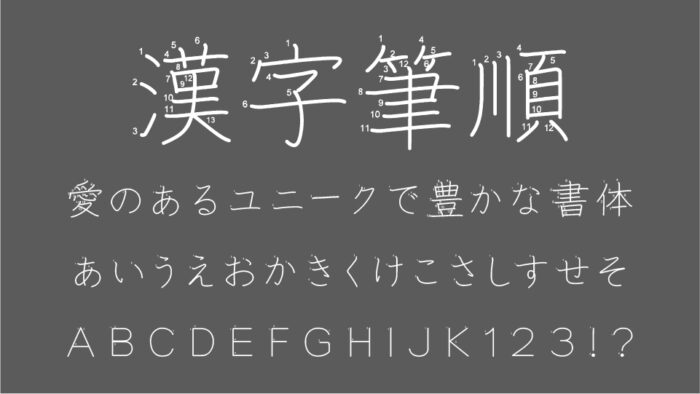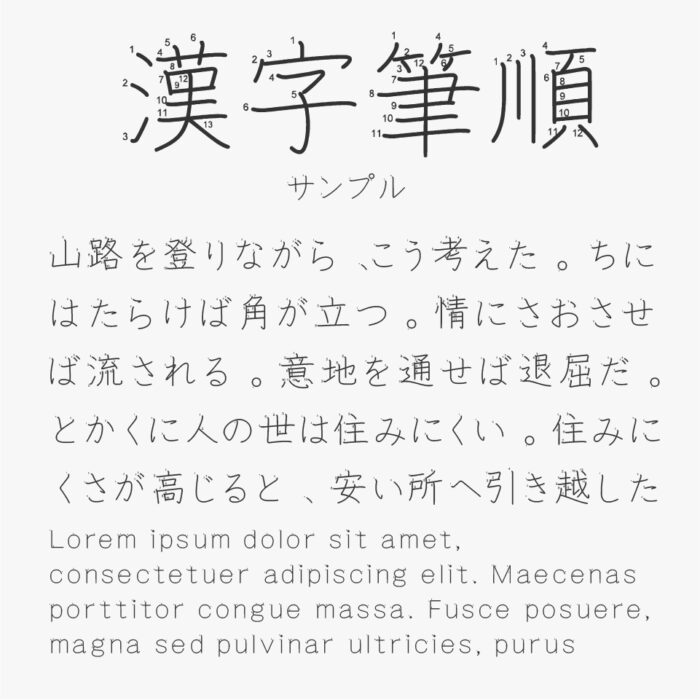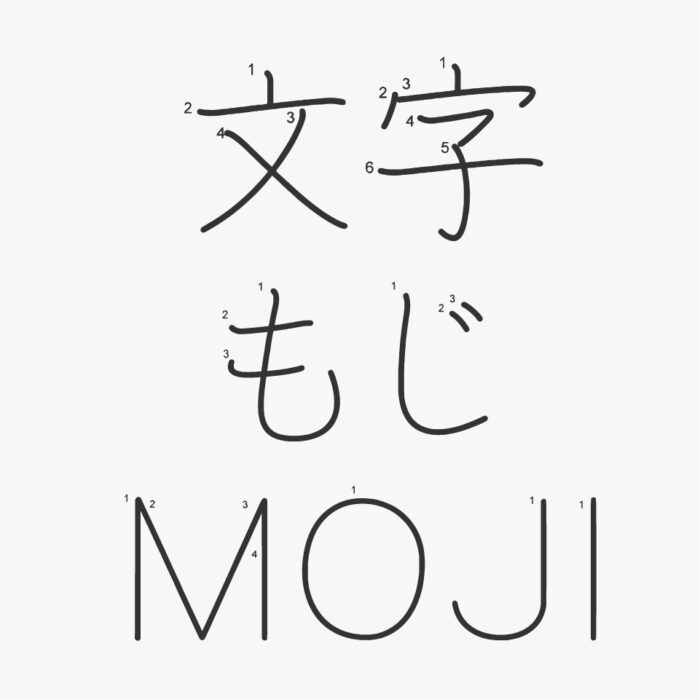
漢字筆順フォント(Kanji Stroke Order Font)
漢字筆順フォントは、文字の筆順が記載されている教育的な雰囲気が合わさった実用性の高い一風変わったフォントです。
細身の筆致で、筆順の数字と矢印がしっかりと添えられており、手書き練習や漢字学習の教材にぴったりです。日本語教師が授業用資料を作成する場合や日本語学習者が筆順の指導を受ける場合など、教育シーンで活用できるフォントとなっています。
大きいサイズ感で使用すると、筆順がくっきり見えます。文字ドリルや漢字ドリルなど宿題を作成するような教育場面にぴったりです。
| 漢字 | ○(6,500字以上の漢字) |